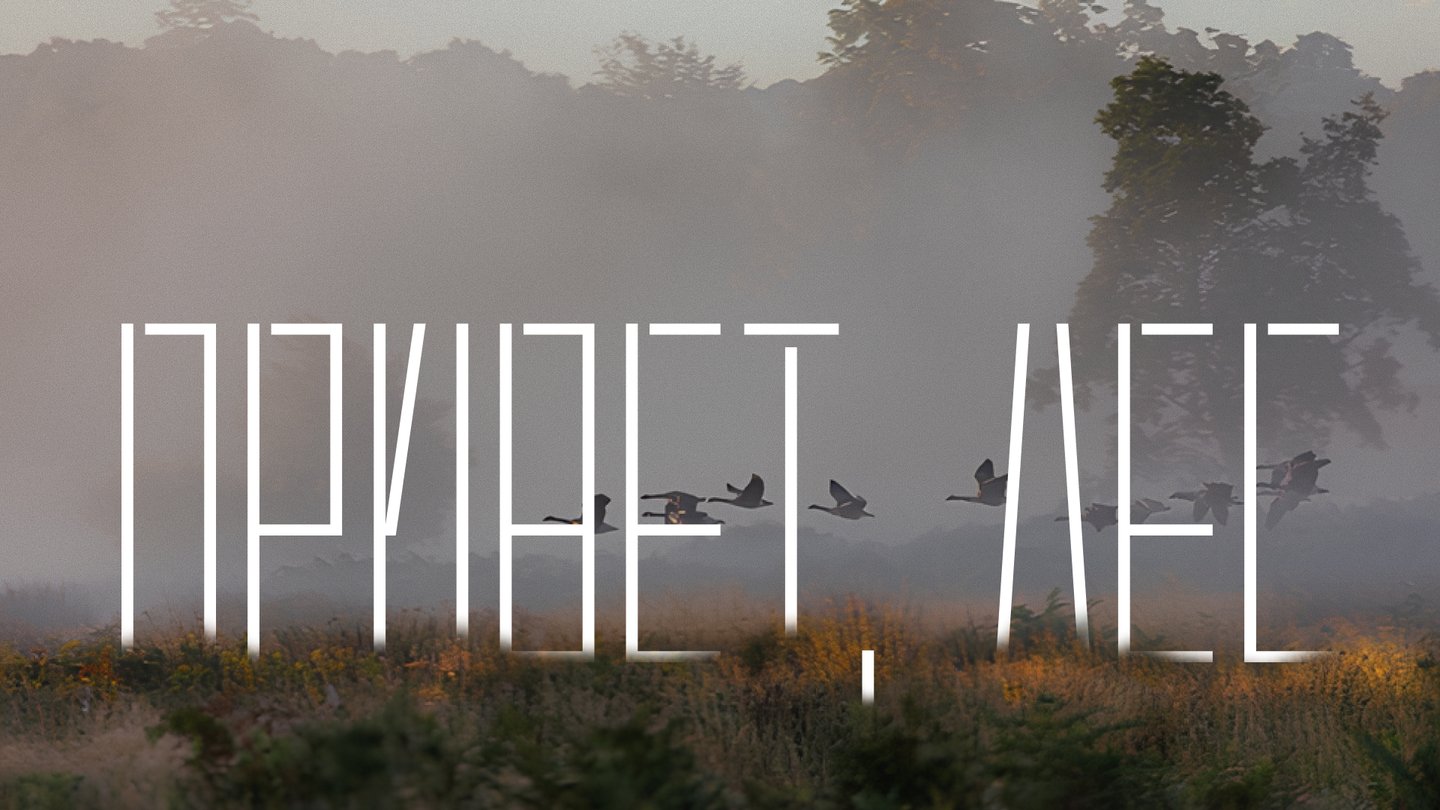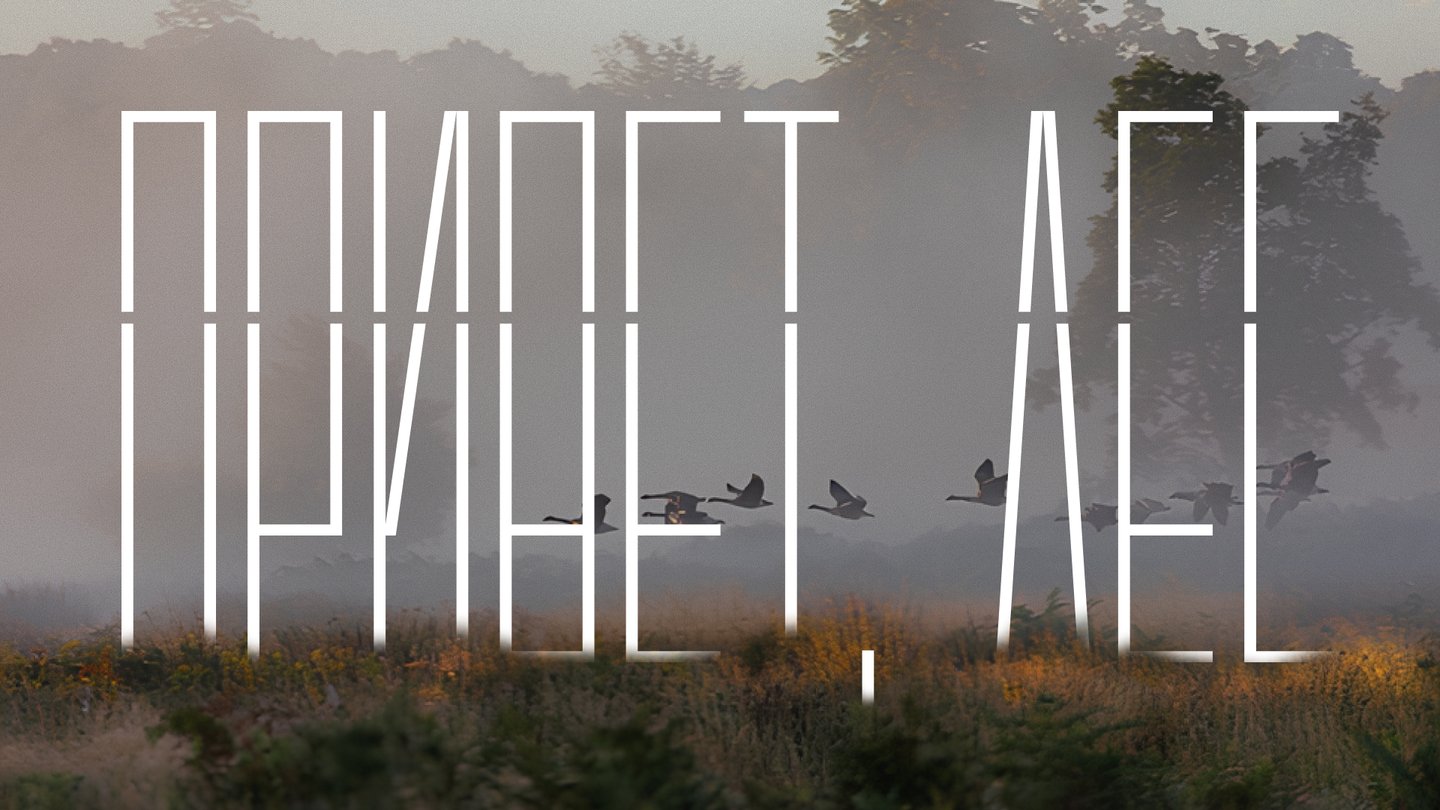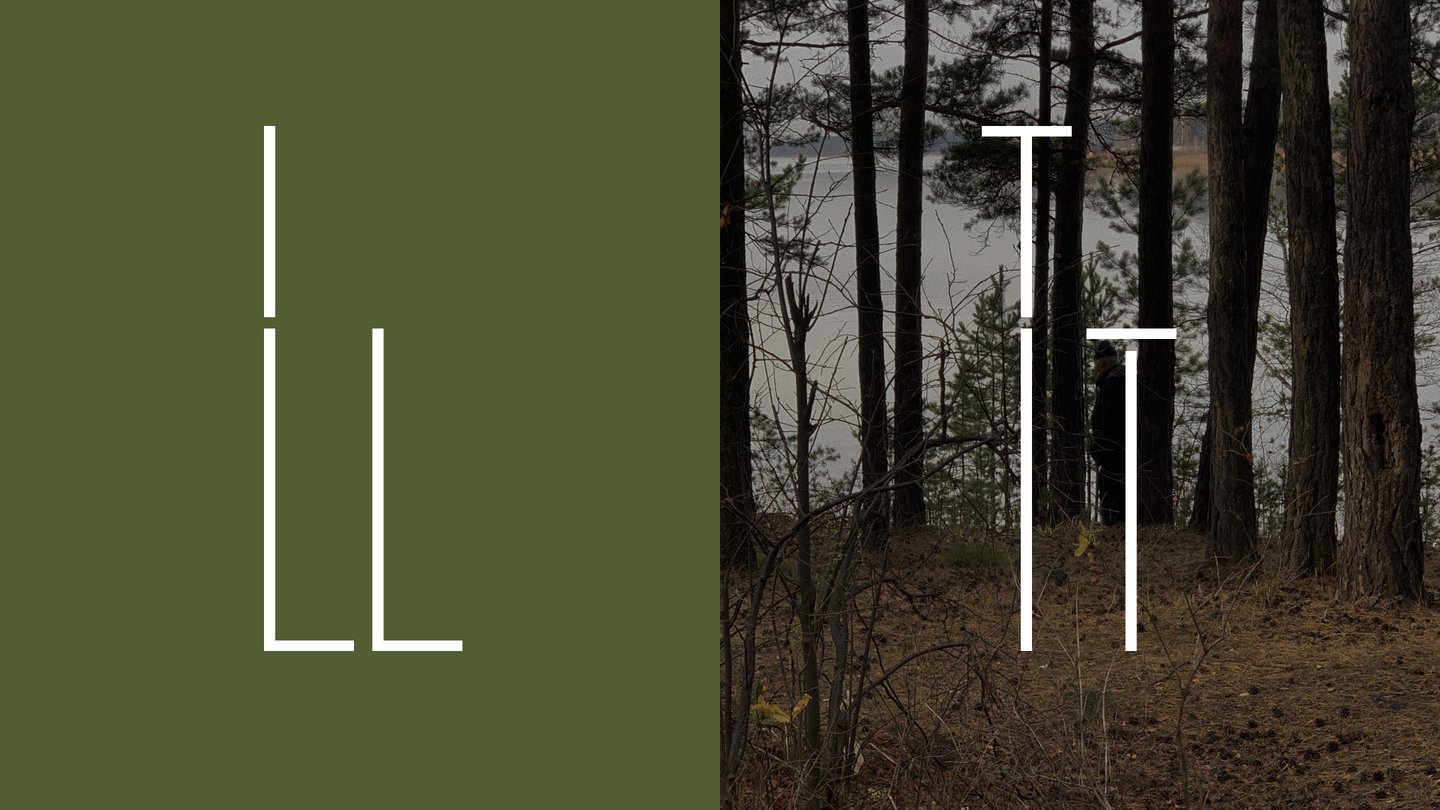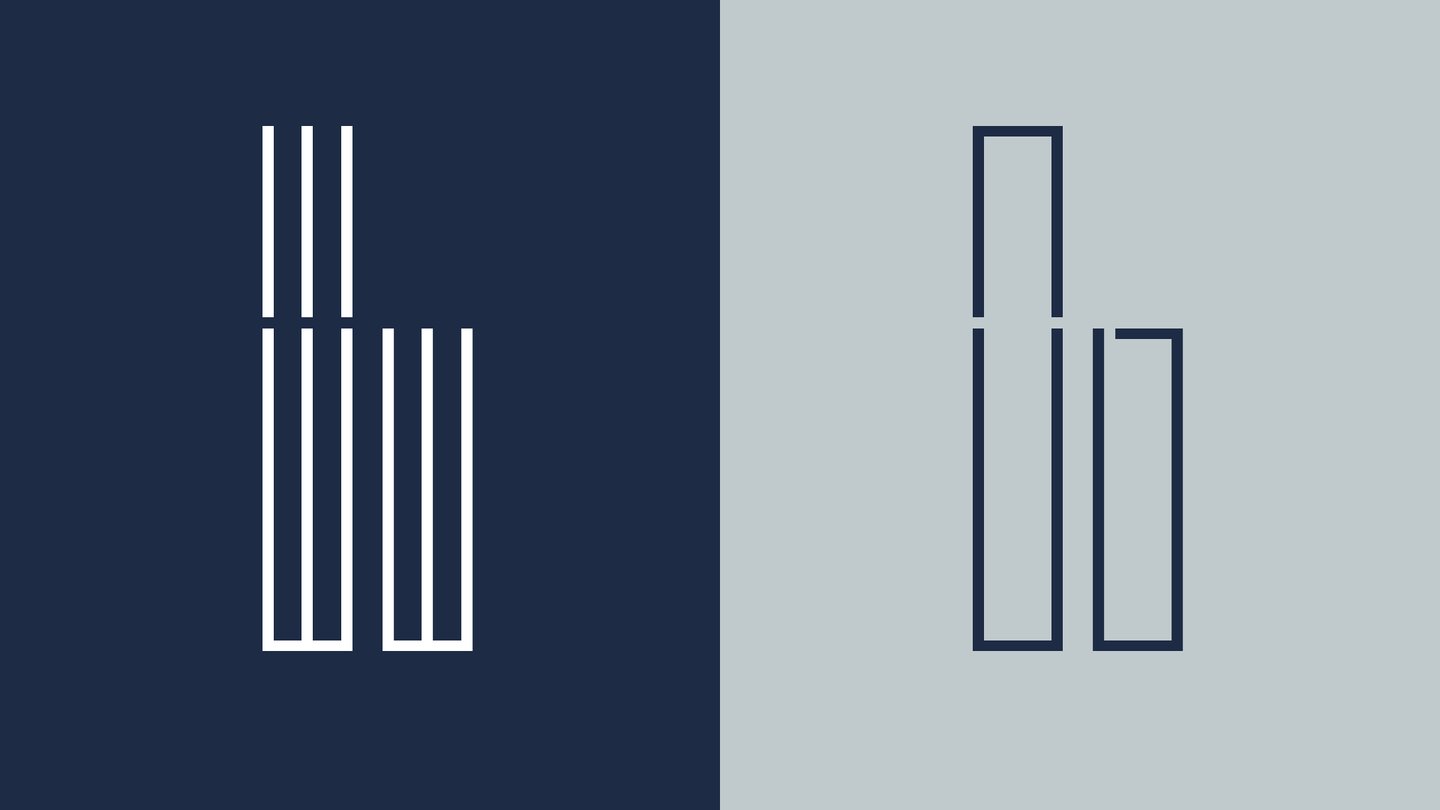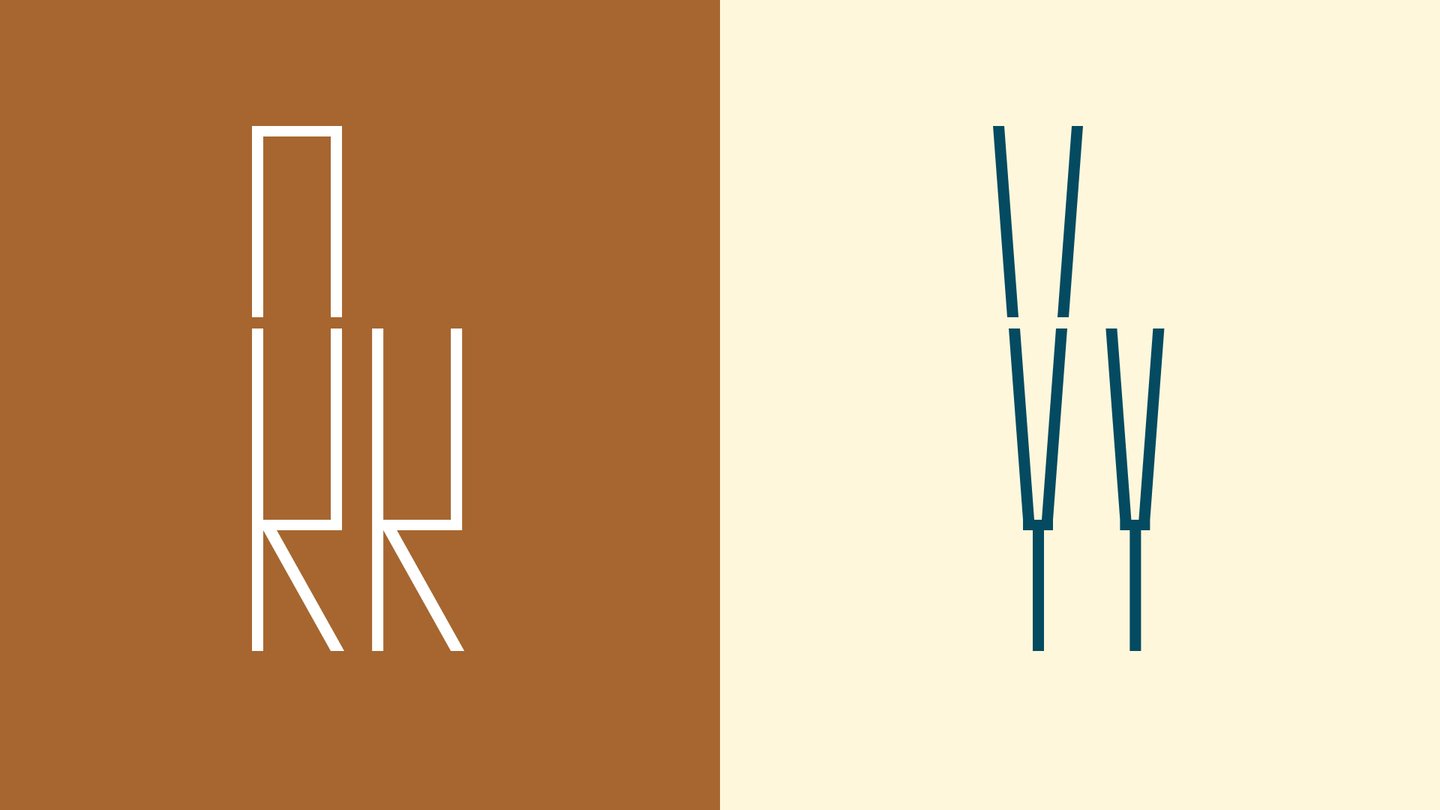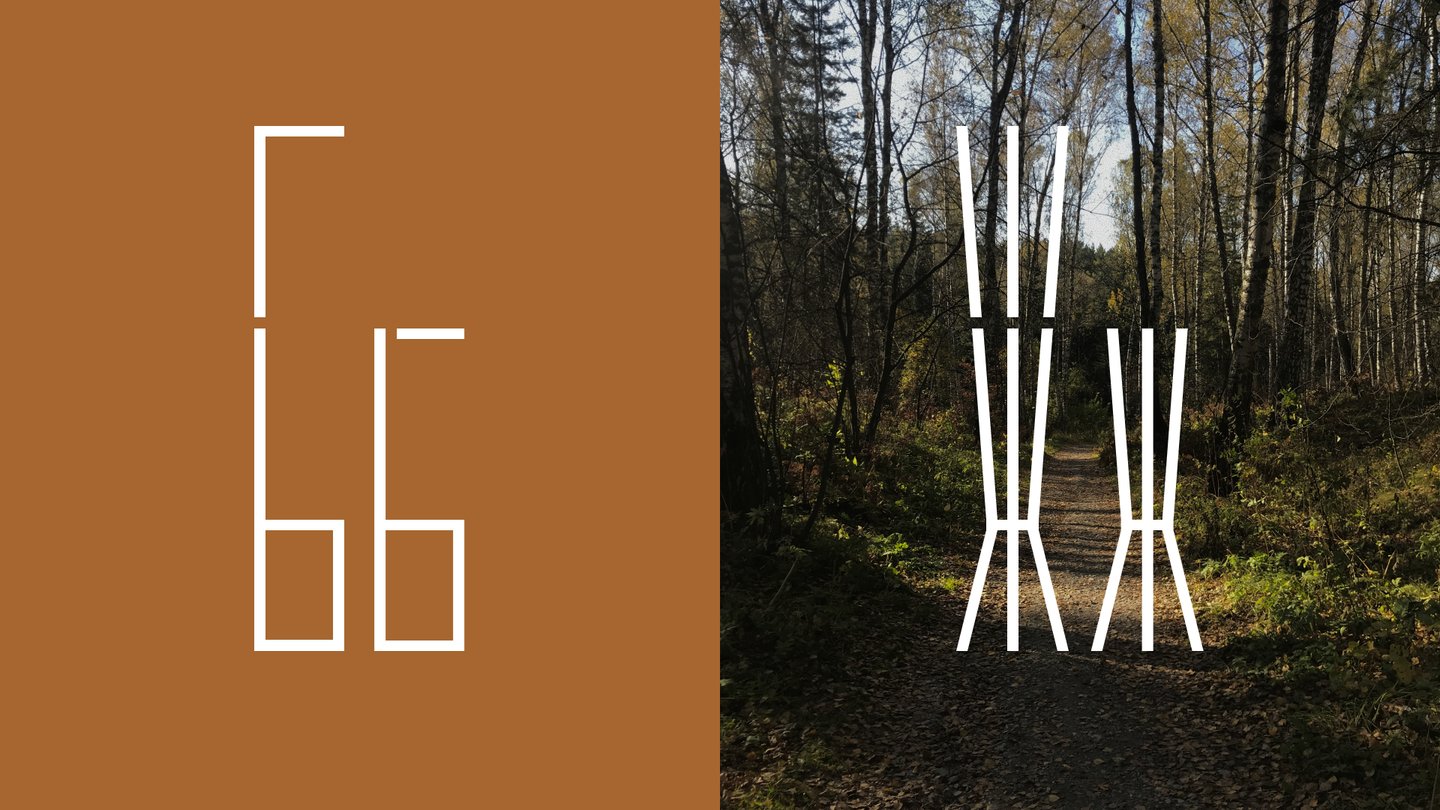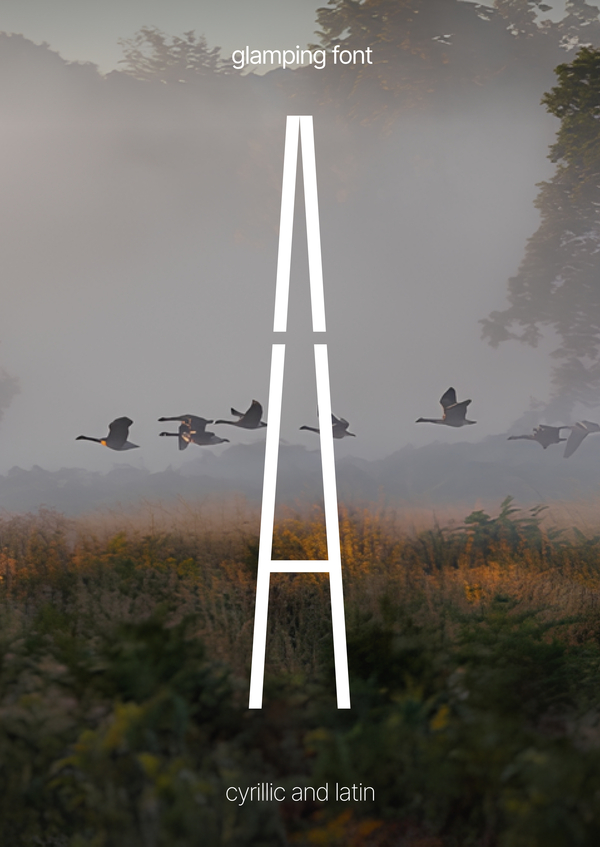
Моноширинный акцидентный шрифт для глэмпингов, который создаётся на принципах модульности, где каждая буква воспринимается как сборная конструкция. Если сократить площадь заглавных букв, то получатся прописные.